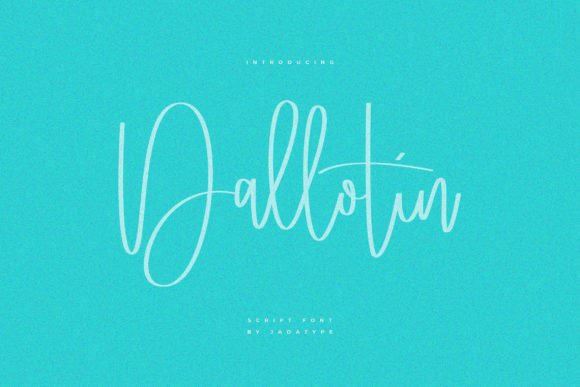
Dallotin
Dallotin์™€ ๊ฐ™์€ ๊ณ ํ’ˆ์งˆ ์ž์‚ฐ์„ ์ฐพ๊ณ  ์žˆ๋‹ค๋ฉด ์ด ํ”„๋ฆฌ๋ฏธ์—„ ํŒจํ‚ค์ง€๋Š” ์ฐฝ์˜์ ์ธ ํ”„๋กœ์ ํŠธ๋ฅผ ์œ„ํ•œ ํ™˜์ƒ์ ์ธ ์„ ํƒ์ž…๋‹ˆ๋‹ค.
์ •๋ฐ€ํ•˜๊ฒŒ ์ œ์ž‘๋œ Dallotin๋Š” ๊น”๋”ํ•œ ๋ฒกํ„ฐ, ๋ถ€๋“œ๋Ÿฌ์šด ํƒ€์ดํฌ๊ทธ๋ž˜ํ”ผ ๋ฐ ์•ˆ์‹ฌํ•  ์ˆ˜ ์žˆ๋Š” ์ƒ์—…์šฉ ๋ผ์ด์„ ์Šค๋ฅผ ์ œ๊ณตํ•ฉ๋‹ˆ๋‹ค.
POD(์ฃผ๋ฌธํ˜• ์ธ์‡„) ์ œํ’ˆ, ๊ฒฐํ˜ผ์‹ ์ดˆ๋Œ€์žฅ ๋˜๋Š” ์†Œ์…œ ๋ฏธ๋””์–ด ๊ทธ๋ž˜ํ”ฝ์„ ๋งŒ๋“ค ๋•Œ Dallotin๋Š” ์ด์ƒ์ ์ธ ์„ ํƒ์ž…๋‹ˆ๋‹ค.